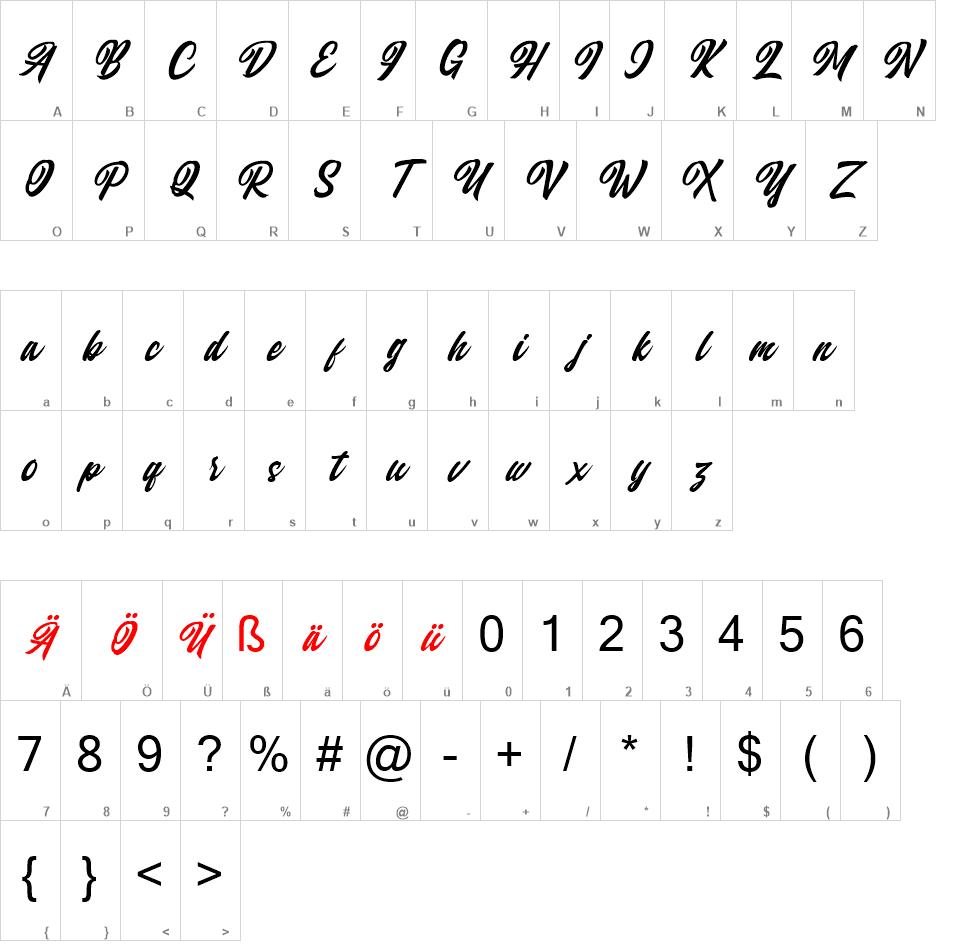
Qintan Script
Qintan Script Inspiriert von Urban, Streetwear und Vintage mit Liebe Handlettering Stil gemacht. Ideal für Branding, Logos, Handschriften, Produktverpackungen, Header, Poster, Merchandise, Social Media Bücher / Titel, Sonderveranstaltungen, etc.